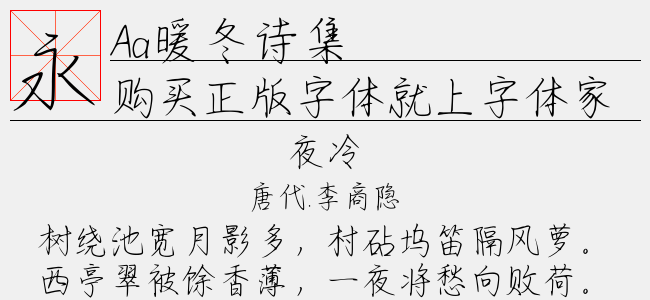
Aa暖冬诗集(6.36 MTTF中文字体下载)
Aa暖冬诗集 字体大小6.36 M,包含了6763个汉字以及附加其他英文字体和阿拉伯数字,属于Aa字体。Aa暖冬诗集(TTF)可以免费下载,商业用途请自行购买版权,它的特征就是手写,钢笔,极细,手书风格,采用安装嵌入的安装方式,支持符号拉丁文日文中文等语言
字体作者:Aa字体
字体名称:Aa暖冬诗集